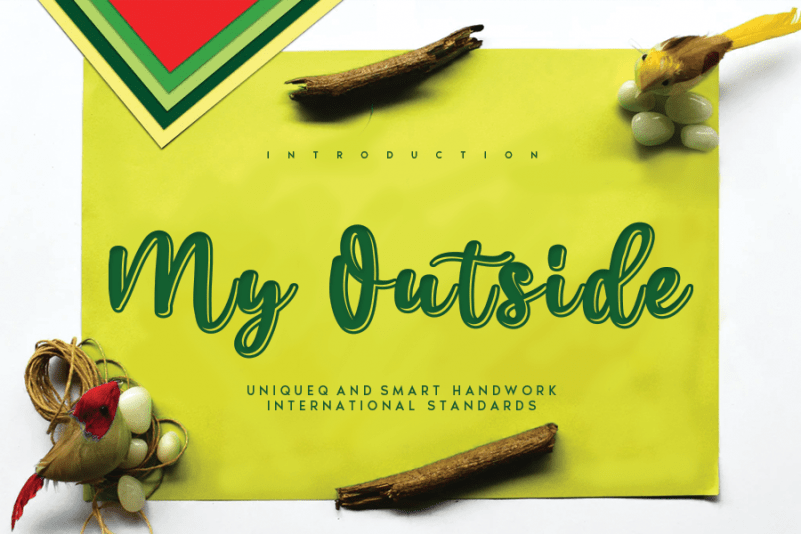
My Outside Script Font
My Outside Script Font é uma elegante fonte escrita à mão que transmite sua própria singularidade única e seu estilo inegavelmente sofisticado. Perfeita para seus trabalhos favoritos, essa fonte se destaca por suas características fluidas e perfeitamente equilibradas. Suas letras parecem ter sido criadas por um artista de verdade, cada traço carregando sua própria história e arte. É a escolha perfeita para criar design impressionante, seja em cartazes urbanos ou em trabalhos de design gráfico profissional. Atrairá qualquer visualizador que encontre seu estilo autêntico e deslumbrante. Não importa qual projeto você está desenvolvendo, My Outside Script Font certamente fará a diferença.